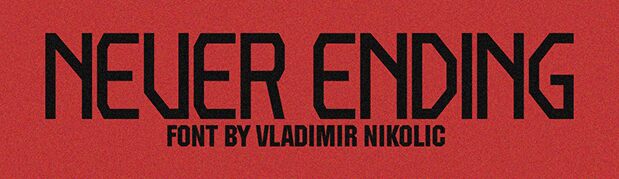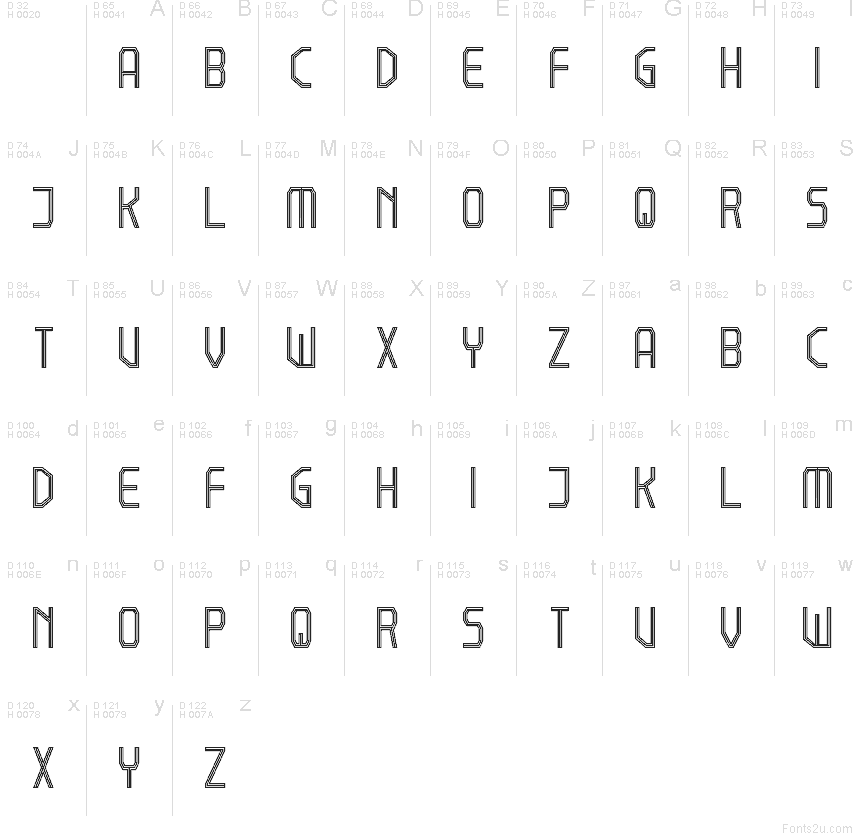
Never Ending Retro Regular
Never Ending Retro от Vladimir Nikolic - это бесплатный техно-шрифт для заголовков с высокими узкими буквами, очерченными вложенными линиями. Повторяющиеся полосы, острые углы и открытые центры придают ему точную, почти «аркадную» структуру, которая выглядит четко и выразительно.
Never Ending Retro отлично подходит для логотипов, заголовков на плакатах, музыкальных обложек, рекламных листовок, игровой графики и упаковки, где требуется яркий ретро-техно стиль. Многослойный контур шрифта также уместен в вывесках, редакционных акцентах и коротких фразах, где форма букв берет на себя основной визуальный акцент.